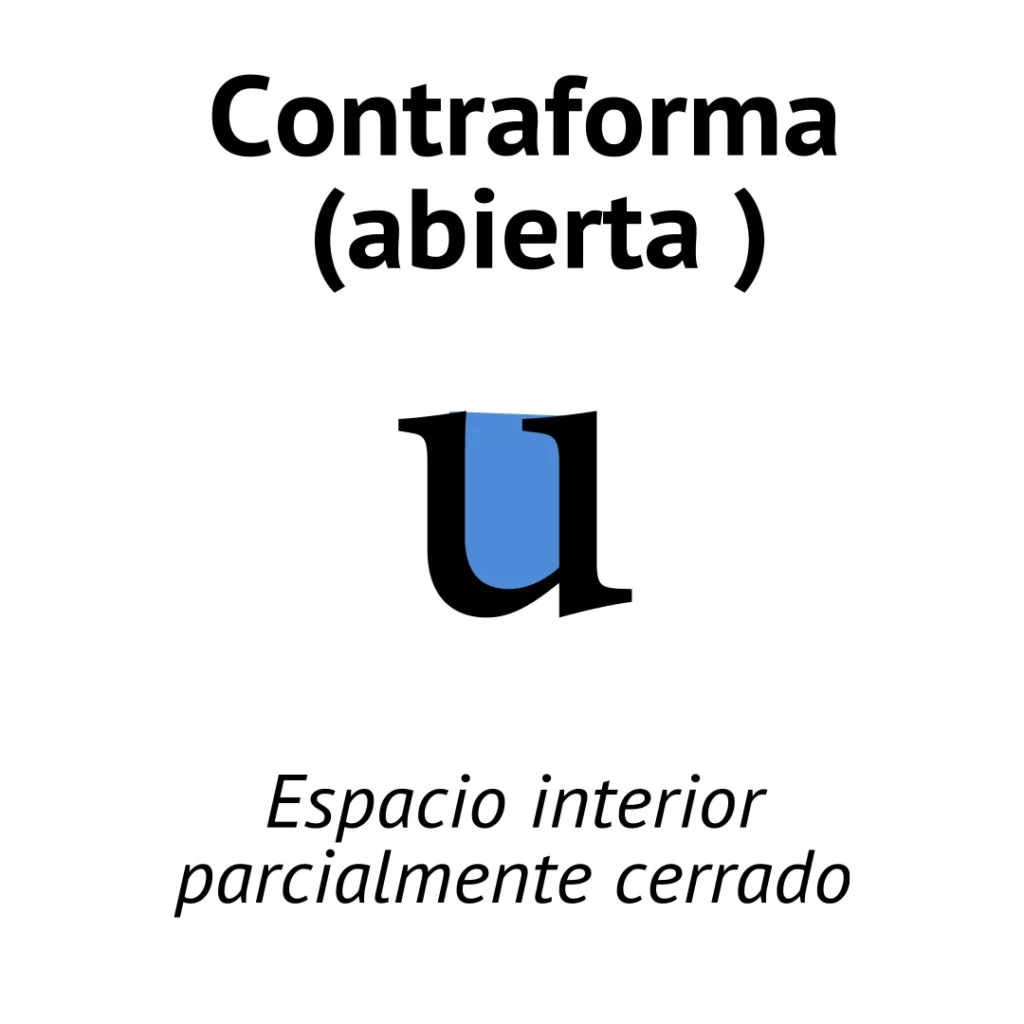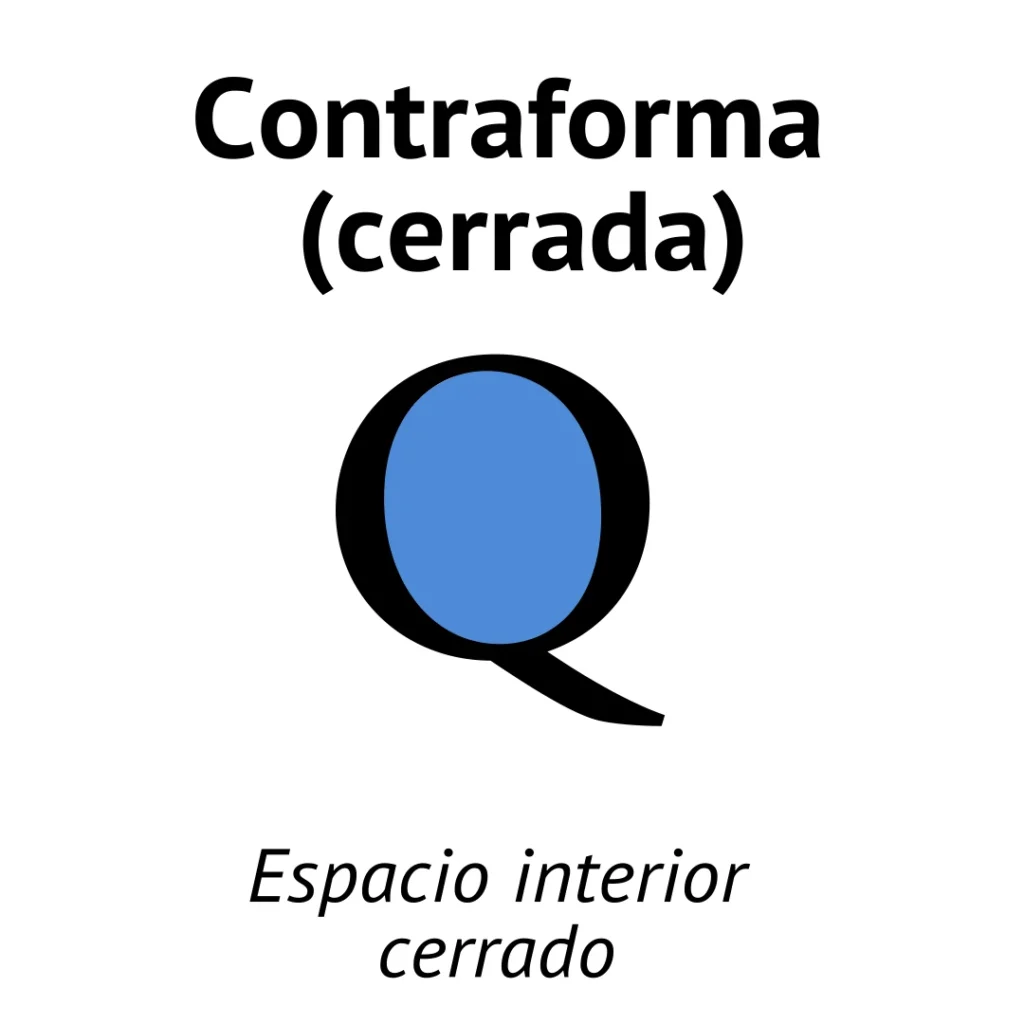
Es el espacio interno de una letra, parcial o totalmente cerrado.
La importancia de la contraforma radica en su relación con la forma de la letra, y cómo los ajustes que modelan este espacio blanco entre caracteres se relaciona con la legibilidad de un texto.